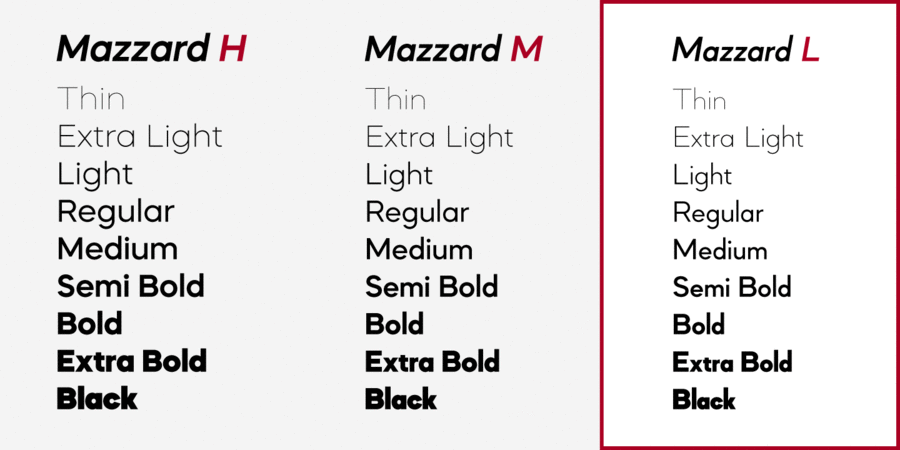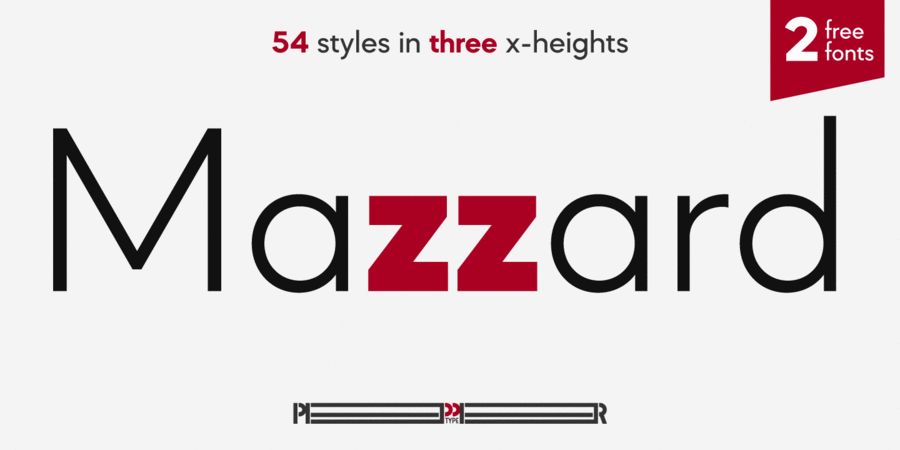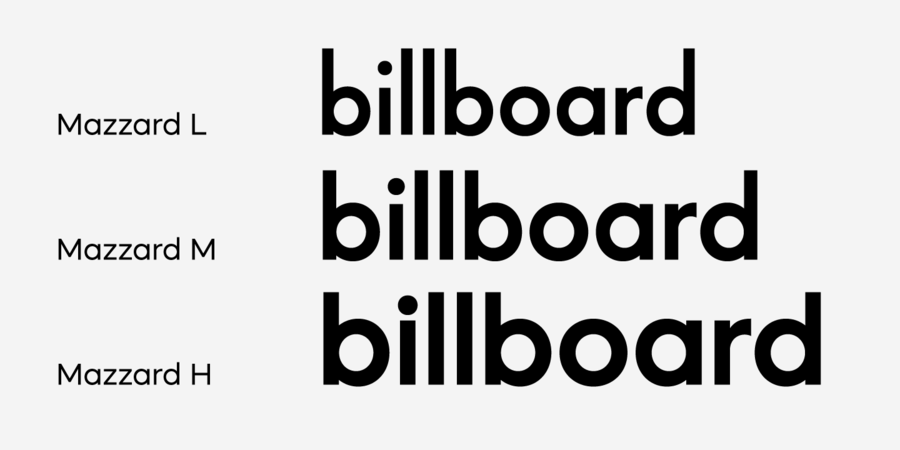
Mazzard L – частина шрифтового суперсімейства Mazzard, яка має маленьку висоту рядкових знаків. Суперсімейство складається з трьох геометричних гротесков з різним x-height. Mazzard L має широкий спектр підтримки мов та пропонує великій вибір альтернативних гліфів. Шрифт розробив Олег Ліщук в 2019 році.
Асоціації з сімейством шрифтів Mazzard LОсобистість і характер гарнітури:
точний, рівний, статичний, стійкий, штучний, інженерний, міський, різкий, чіткий, креслярський, чистий, гострий, тонкий, дротяний, скляний, легкий, прохолодний, ясний, невагомий, прозорий, крихкий, модний, худий, технічний, урбаністичний, твердий, позитивний, якісний, популярний, гладенький, впевнений, сильний, переконливий, індустріальний, техногенний, архітектурний, залізний, сталевий, важливий, мотивуючий, залізничний, амбітний, яскравий, помітний, активний, потужний, важкий, щільний, тісний, монументальний, гучний, сміливий
креслення, дизайн, лосьйон, туалетна вода, мода, прилад, інженер, Місто, архітектура, урбаністика, конструктор, коворкінг, меблі, інтер'єр, кафе, кіно, техніка, інструмент, промисловість, завод, архітектор, новини, двигун, електростанція, енергетика, прес, металургія, взуття, залізниця, гра, торгівля, атракціон, шоу, телебачення, прапор, мотор Гарнітура має ознаки стилів: